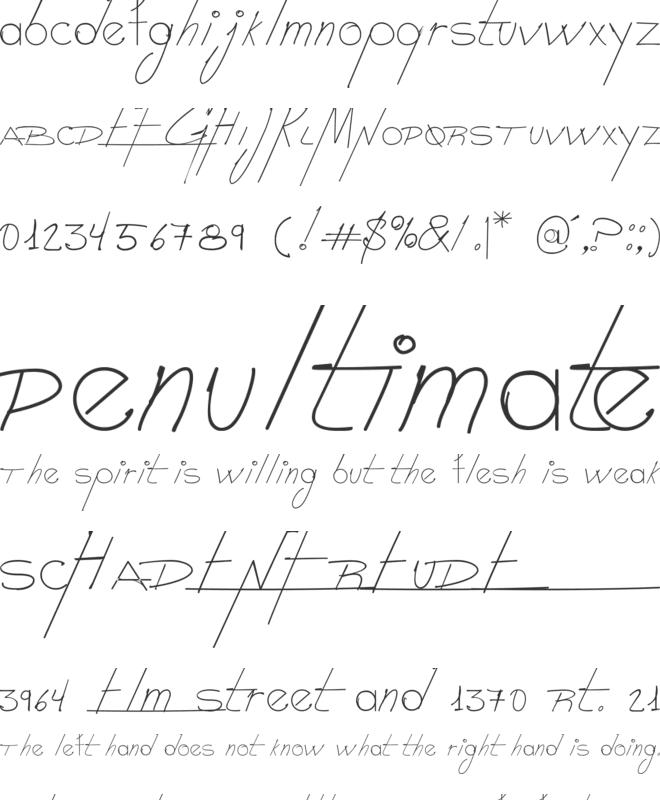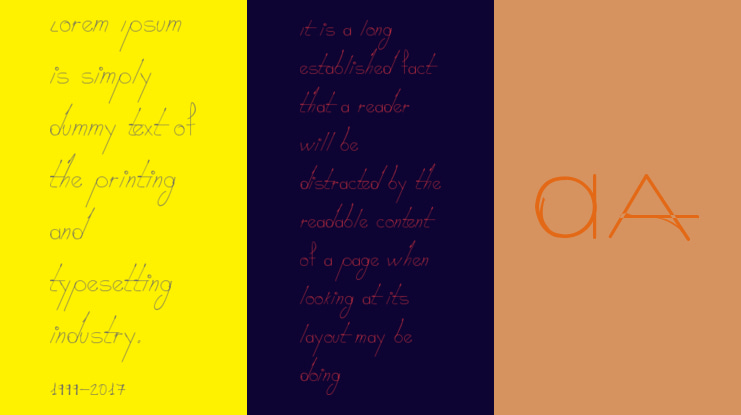
Good night Font
Esta es una tipografía que diseñé inspirada en mi escritura.
This is a font I design inpired in my own writing. If you liked it feel free to use it.